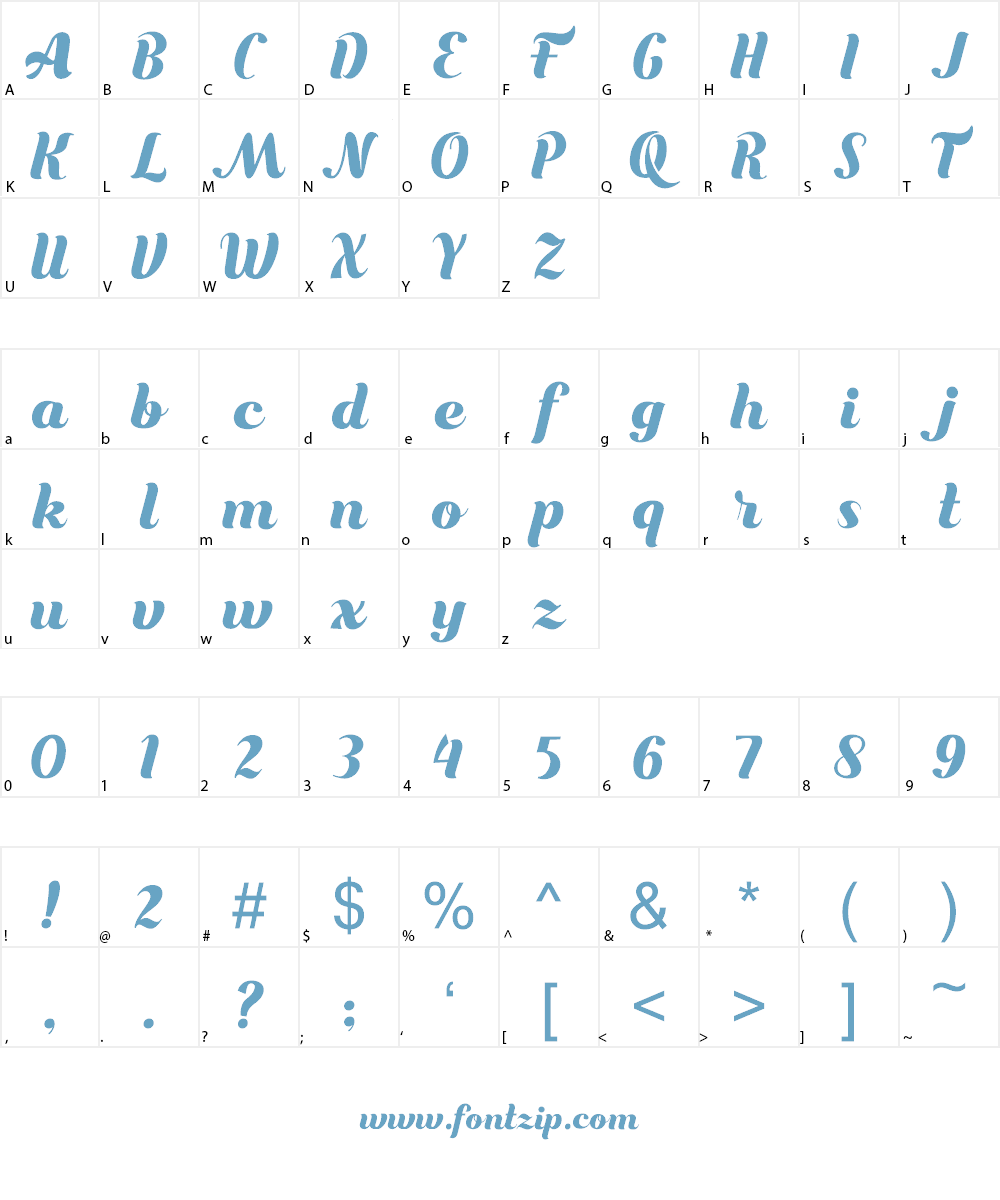
Bungasai diambil dari bahasa Banjar, bungas ai, yang digunakan untuk memanggil seseorang yang cantik atau tampan (bermaksud memuji). Fontasi ini adalah fontasi pertama saya yang dirancang dalam waktu yang cukup panjang, kalau dibandingkan dengan fontasi-fontasi saya yang terakhir.